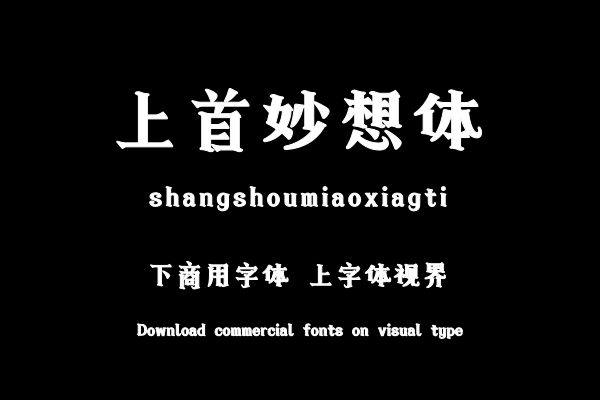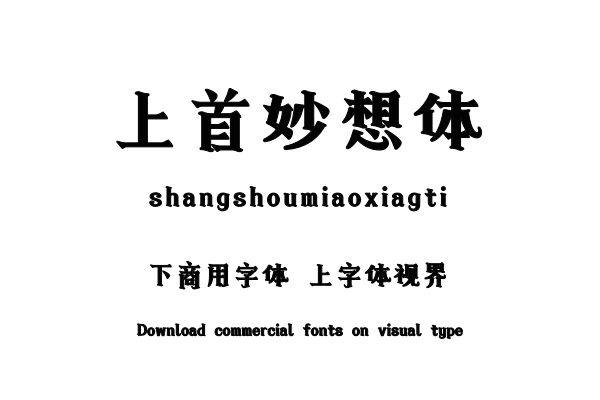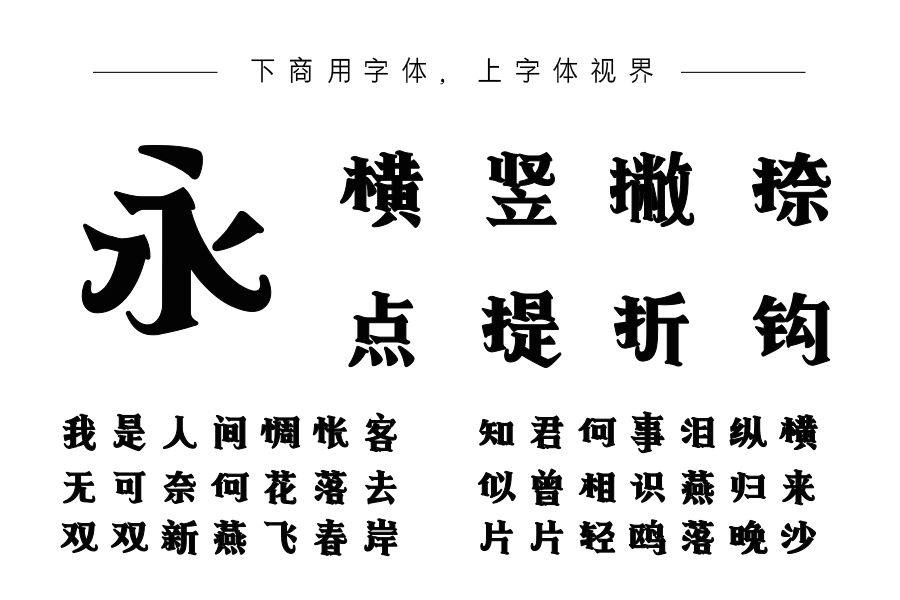
上首妙想体,字体线条粗细变化明显。字形大大小小,形色不一,高低错落,跌宕有致,呈现独特的艺术风格。购买须知:“下载服务费”与“字体VIP”所获得字体 仅用于个人非商用, 商用请联系付费授权。本字体为电脑用字,手机没有root权限不支持直接手机换字(手机如何root,请自行百度搜索教程)。购买前请先 了解清楚后再付款 ,字体为虚拟产品无法回收 一旦购买不支持退款。